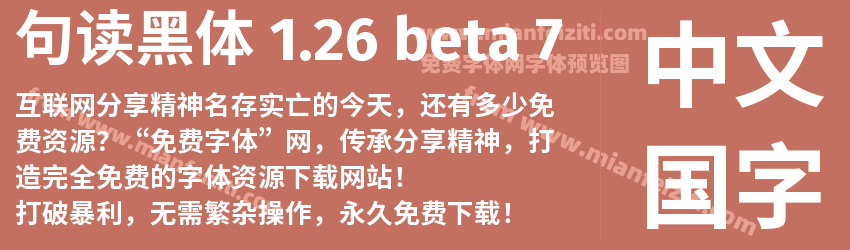
句读黑体 1.26 beta 7
句读黑体,支持多种语言文字的商用免费开源黑体,基于更纱黑体、思源黑体、尙古黑体、Noto Traditional Nushu、KhaWa Sans 和 FiraGO。
支持的文字
• 汉字
• 假名
• 谚文
• 女书
• 藏文
• 拉丁文扩展
• 西里尔文扩展 (包含塞尔维亚语和保加利亚语的 Opentype locl 特性)
• 希腊文扩展
• 国际音标
• 阿拉伯文
• 天城文
• 格鲁吉亚文
• 希伯来文
• 泰文
字体名称解读
• 按照风格划分
• 句读黑体: 使用占 1 个汉字宽的引号(“ ”)、双层 g、开放字怀 4 和不等宽数字
• 句读黑体 UI: 使用占半个汉字宽的引号(“ ”)、单层 g、封闭字怀 4 和等宽数字
• 按照字形划分
• Hans: 国标字形
• Hant: 传承字形
• Jpan: 日本字形
• Kore: 韩国字形